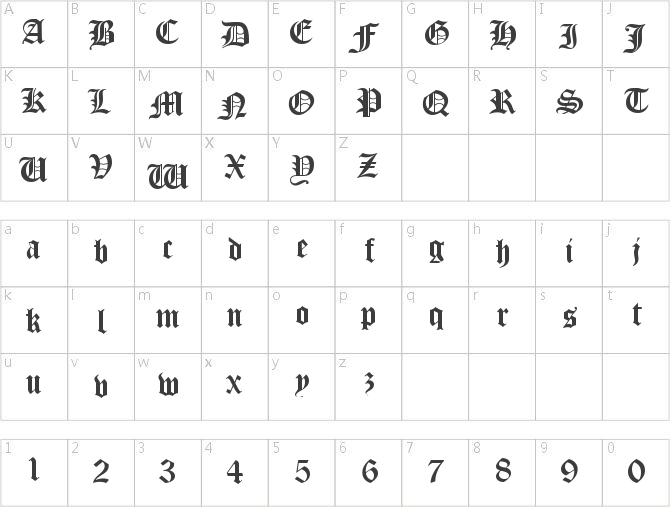
字體名稱: Midevil
Midevil-Extended-Normal
Midevil-Extended-Normal字體字庫(kù)是一款讓人賞心悅目、百看不厭的英文字體,適合各類廣告和產(chǎn)品包裝設(shè)計(jì)應(yīng)用,字體大小0.06MB,格式為ttf字體,上傳用戶是17199970014,作者/版權(quán)方為未知